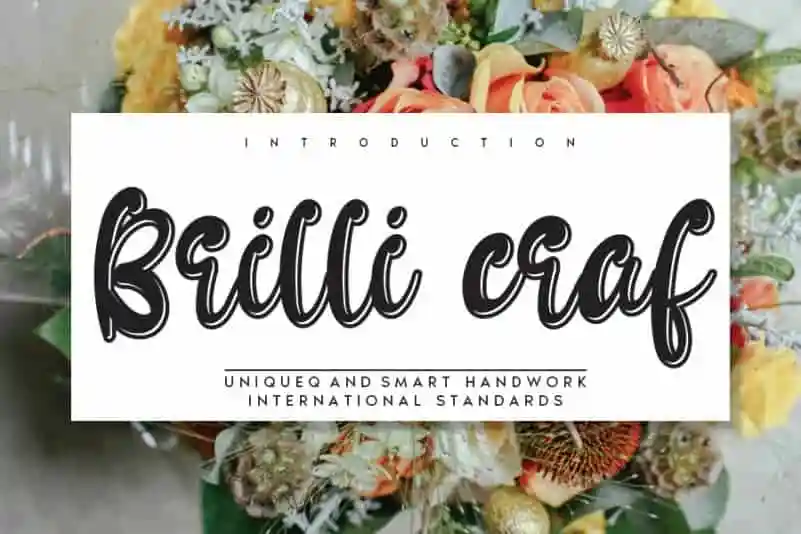
Brilli craf Display Font – Download Grátis
Brilli craf Display Font é uma fonte capaz de transformar qualquer projeto visual em destaque, seja ela para cabeçalhos grandes ou textos mais amplamente distribuídos que exigem um desafio gráfico. Ideal tanto para web quanto impressão, Brilli Craf pode adaptar-se à variedade de tamanhos e estilos necessários ao longo da página. Seja você criando conteúdo para as telas em movimento ou desenvolvendo materiais tradicionais como livros ou cartazes, essa fonte oferece a capacidade de criar uma impressionante presença visual. Com Brilli Craf, seu design ganha um novo tom de impacto e originalidade. Essa fonte é perfeita para designers que desejam explorar suas habilidades criativas ao criar um estilo único em projetos digitais ou físicos, oferecendo a flexibilidade necessária para adaptar-se a diferentes contextos sem comprometer seu poder visual. Com uma variedade de opções disponíveis, Brilli Craf é a escolha perfeita para quem procura tanto estética quanto versatilidade na sua paleta de fontes.